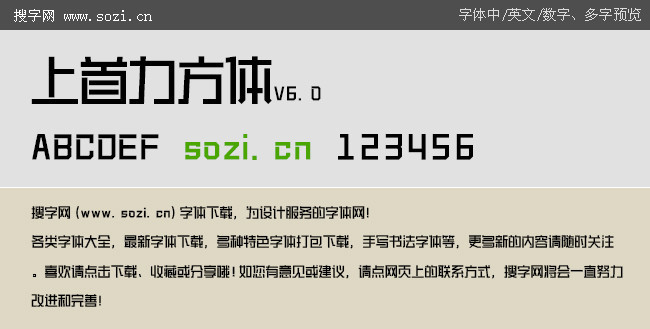
上首力方體V6.0
搜字網(wǎng)給大家提供一款上首力方體中文字體下載,上首酷方體是一款中文藝術(shù)字體,整體字體方正,字橫平豎直,字呈現(xiàn)方塊的感覺(jué)(本版本為升級(jí)版)。適用于搭配標(biāo)志、廣告標(biāo)語(yǔ)、商業(yè)廣告等廣告設(shè)計(jì)。